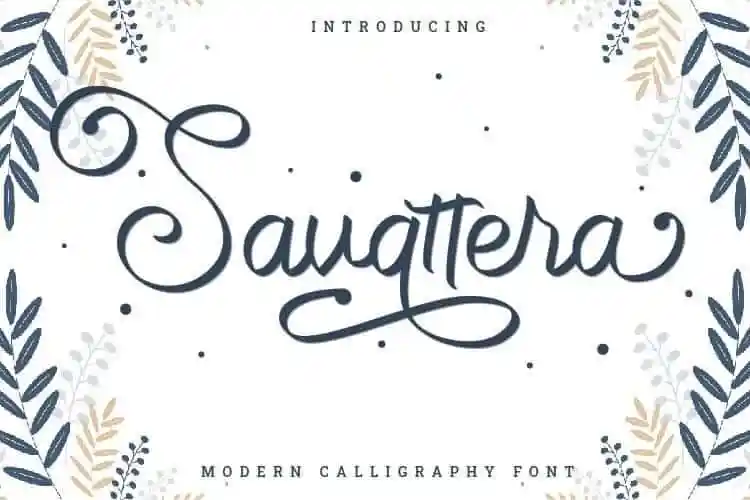
Savattera Handwritten Font – Fonte Grátis
Savattera Handwritten Font
A fonte Savattera Handwritten é uma criação perfeita para quem procura uma fonte com aspecto natural e elegante. Com suas letras completamente desenhadas à mão e ligaturas que permitem reproduzir de maneira precisa o estilo da escrita natural, esta fonte tem um visual atraente e único. Cada caractere é detalhadamente criado por prioritype em 99designs, tornando-a perfeita para várias aplicações como convites para casamento, citações, posts criativos, embalagens de produtos de moda, promoções, imagens prévias de vídeos e logotipos. O design desta fonte é tão versátil que você pode explorar uma variedade de usos sem se estressar, pois ela tem muitas variações interessantes. Seja para um projeto profissional ou pessoal, Savattera Handwritten será uma escolha inteligente para quem valoriza a beleza na escrita e deseja adicionar um toque único a seus designs.